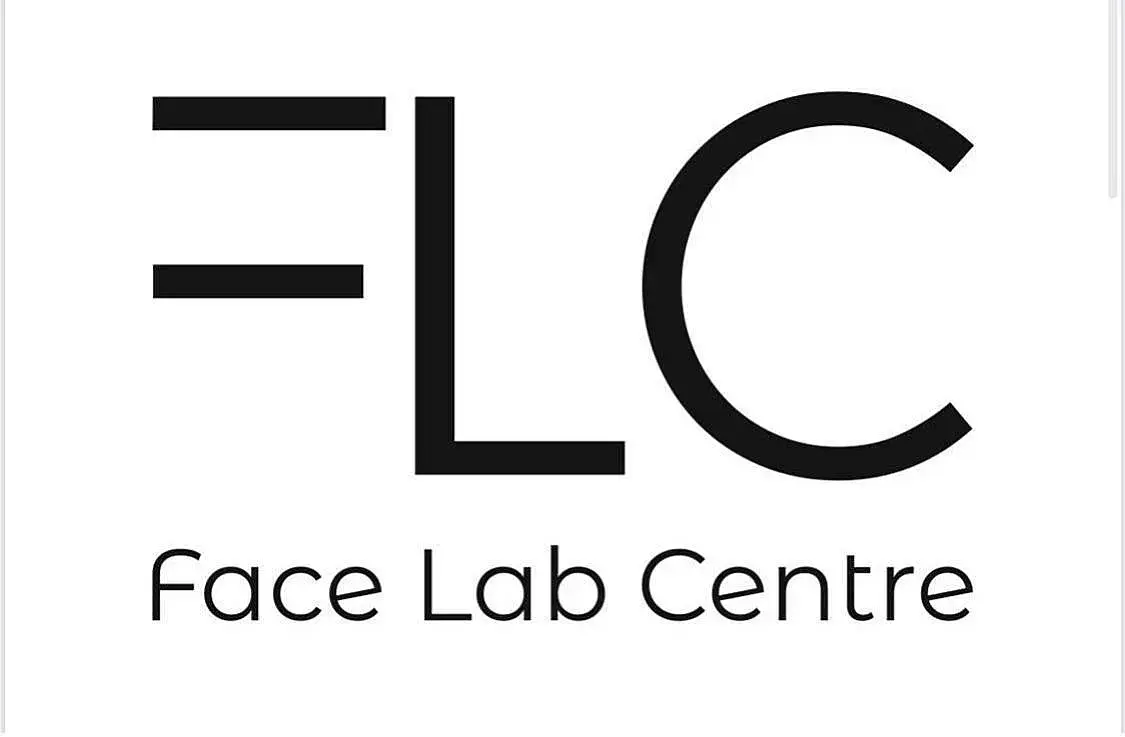
опознать шрифт
возможно не по адресу но может кто знает, чьи загогулины
Побуду капитаном очевидностью, но есть ресурсы которые по картинке определяют шрифт. Делают примерно, как повезет. Сайтов много, надо курить то на одном, то на другом.
Что касается буквы "Фэ", она мне кажется подрезана специально. "Лы" и "Цэ" от шрифта.
мне снизу переписывать надо. букфф не хватает
все нашла вопрос снят